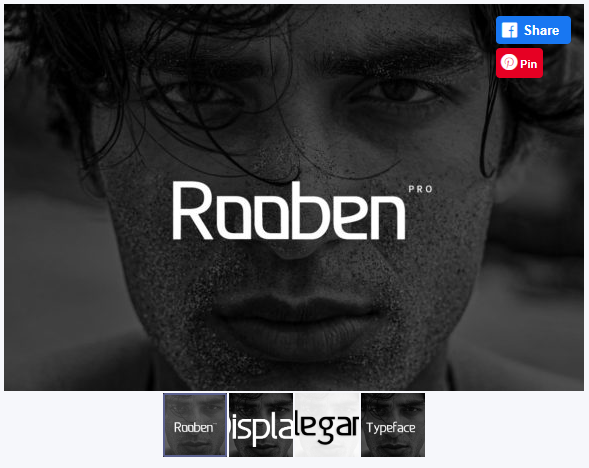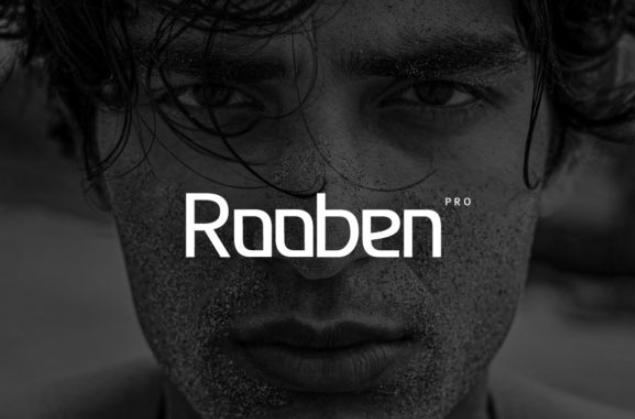
Rooben - это простой и современный шрифт без засечек. Rooben будет отлично смотреться в любом контексте, будь то использование на загруженном фоне или как отдельный заголовок!